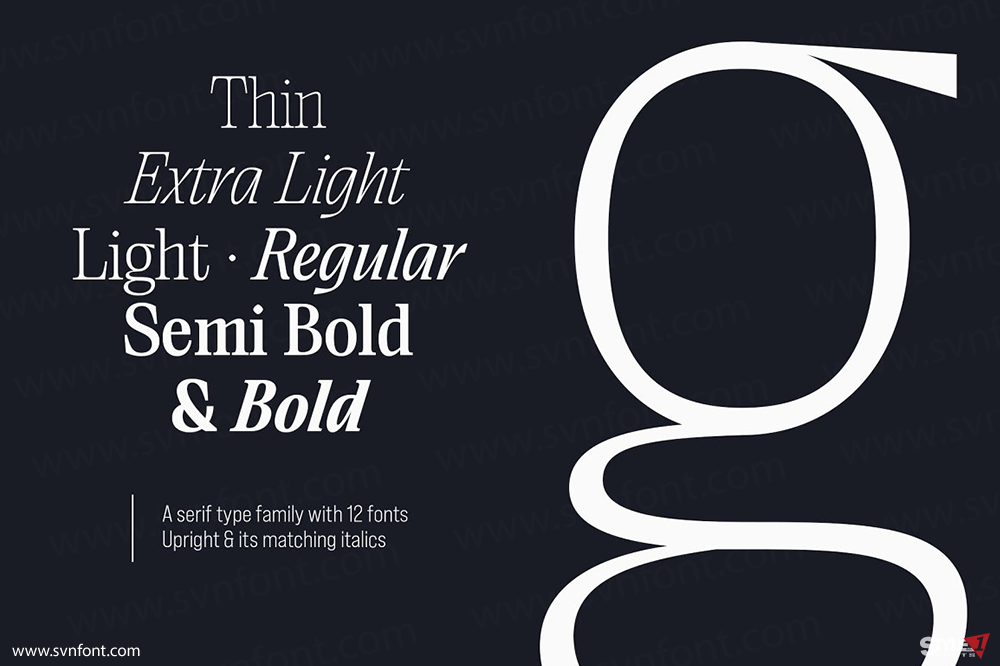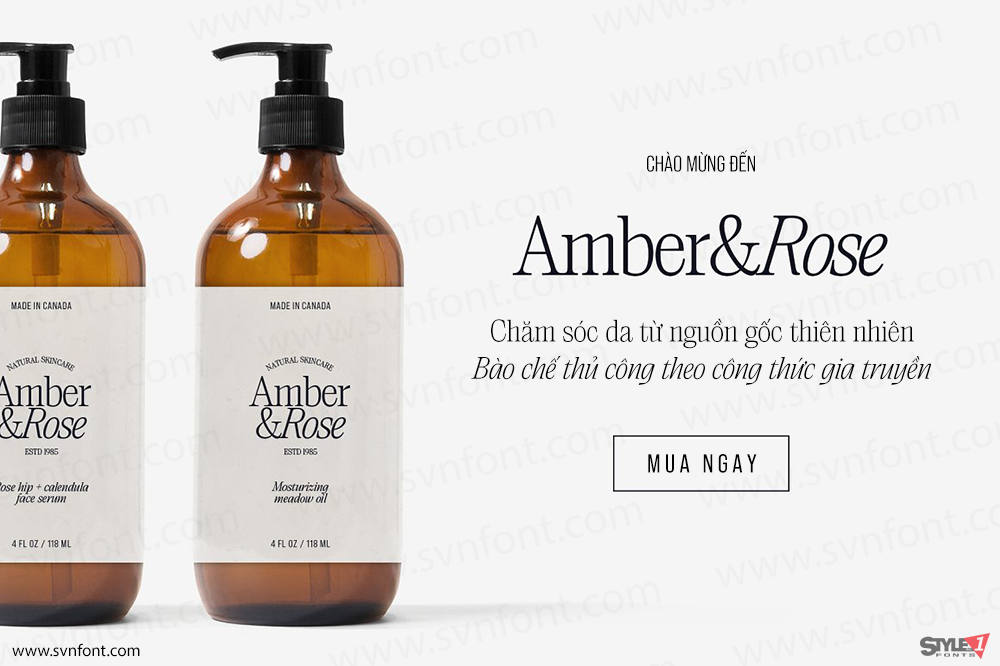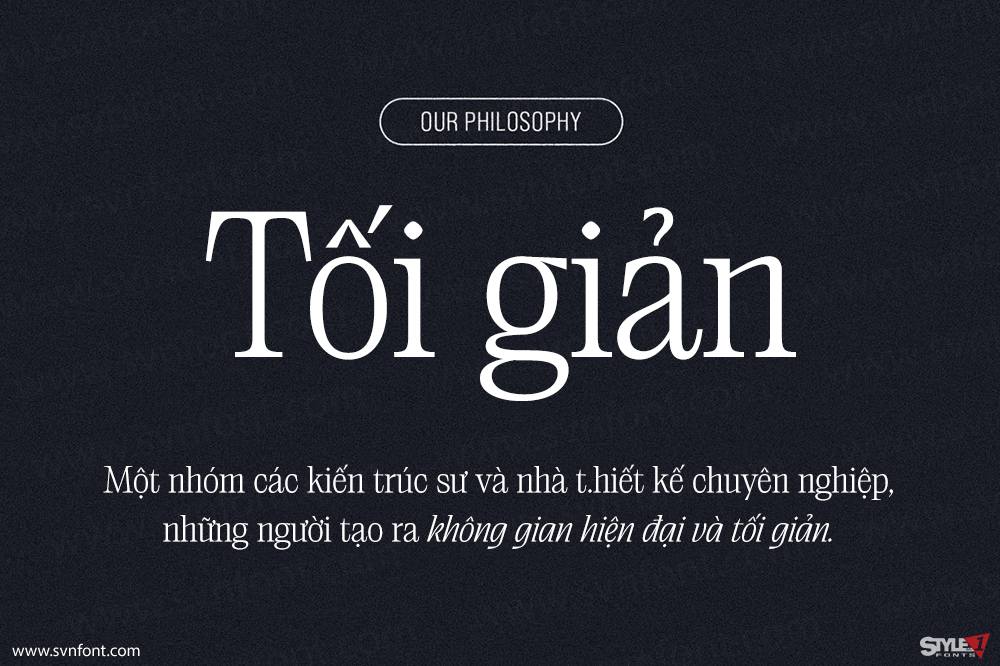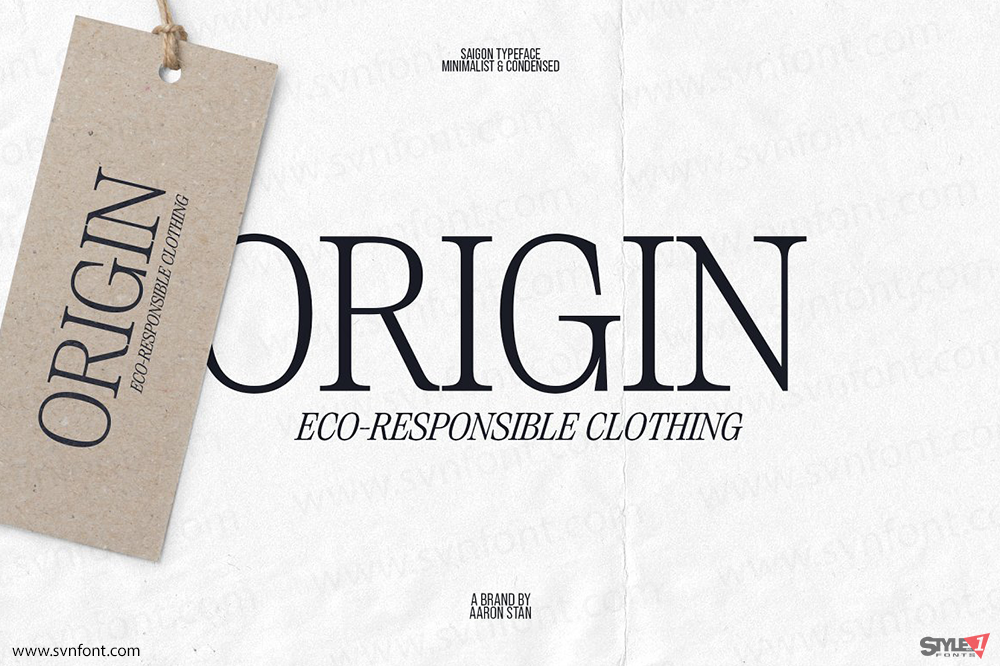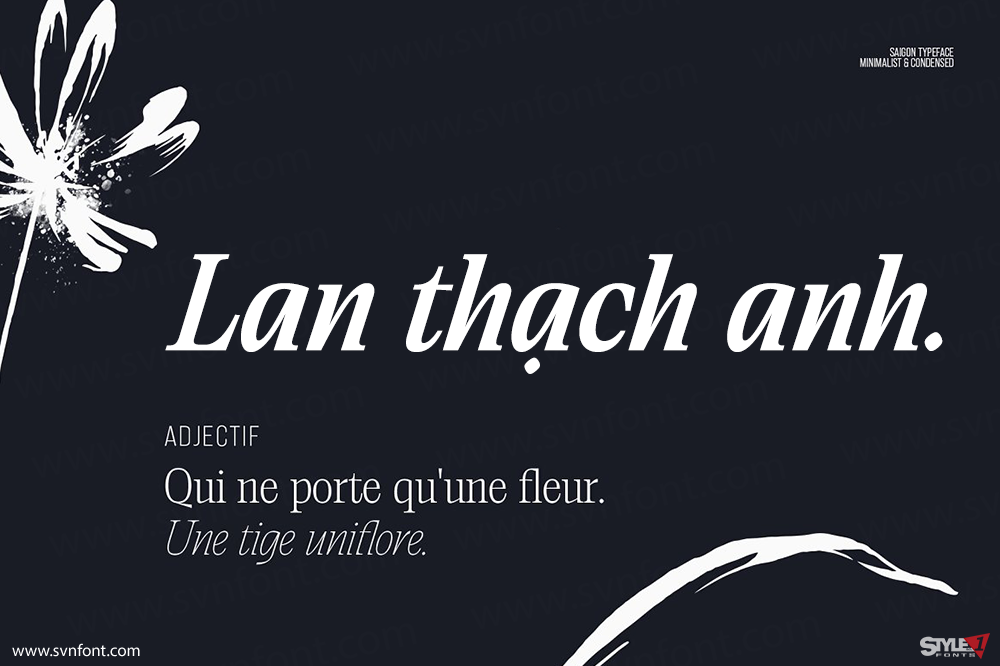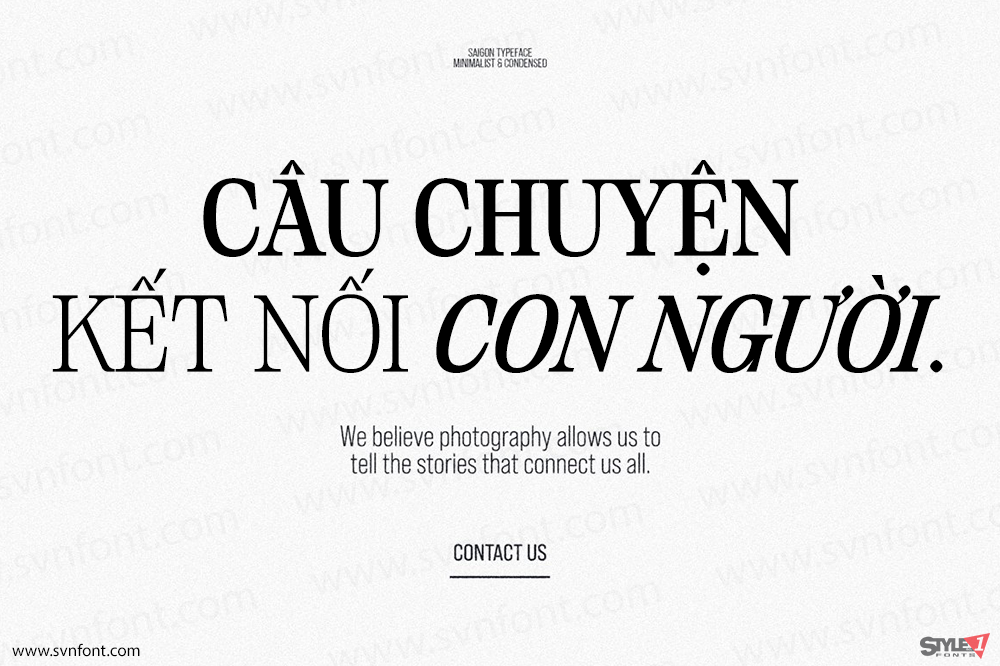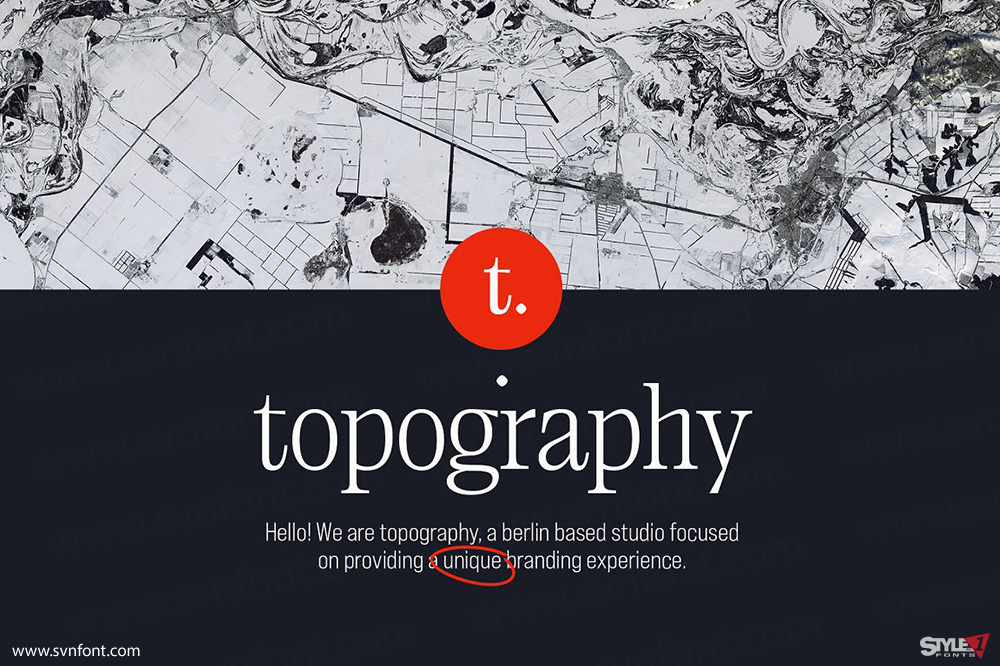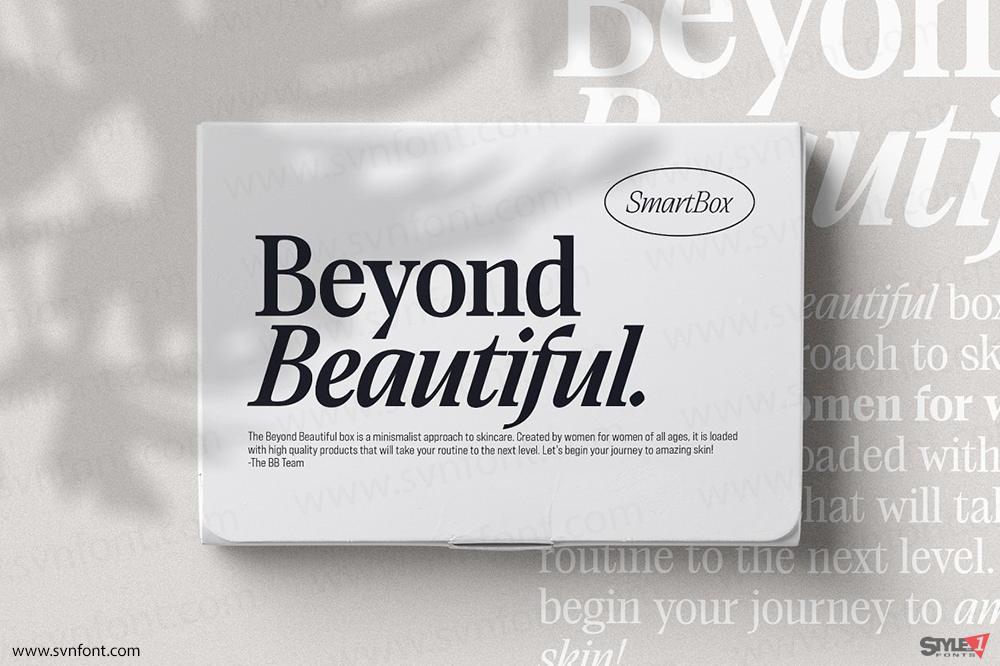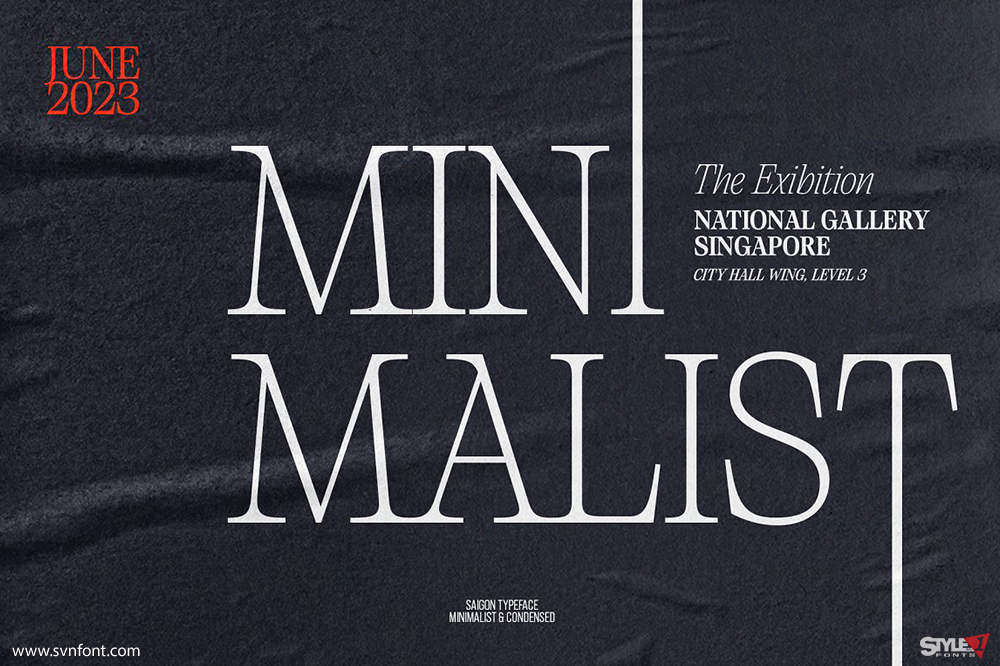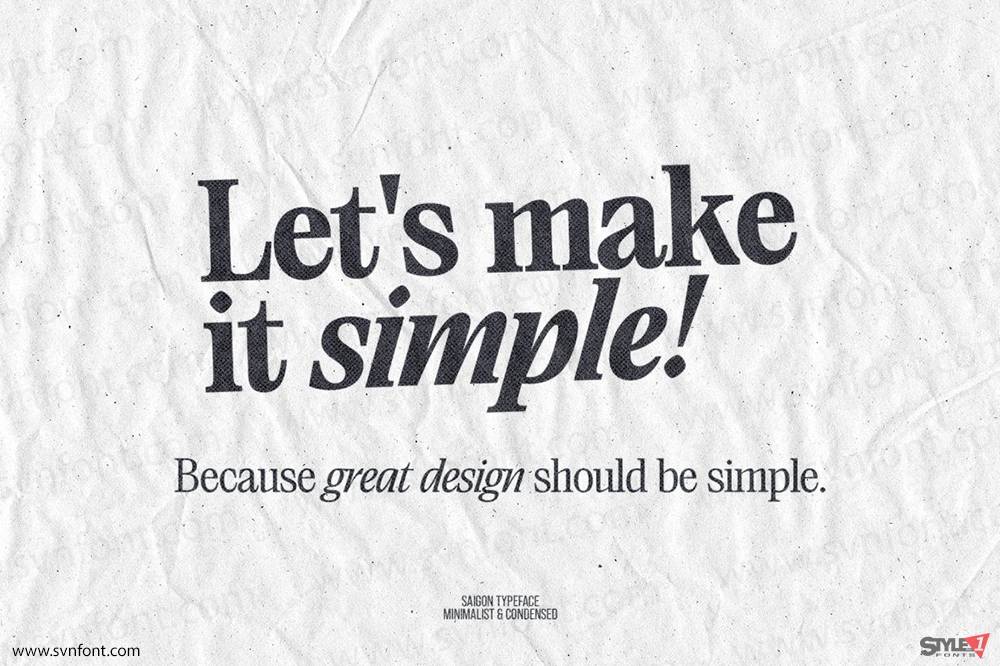
Saigon là một họ phông chữ serif cô đọng tối giản. Với những đường nét thanh thoát và các đường cong chặt chẽ, cá tính của nó nằm ở sự đơn giản, khiến nó trở thành một kiểu chữ biên tập vượt thời gian. Khi chữ nghiêng phá vỡ các nét truyền thống và mang một vẻ ngoài khiêm tốn nhưng hiện đại hơn, nó hòa quyện một cách hài hòa với phiên bản đứng, do đó tạo ra một nhịp điệu hài hòa làm nổi bật phong cách tối giản của Saigon.
Kiểu chữ serif có độ tương phản thấp này được tạo ra để trông tuyệt vời cả trong hiển thị và văn bản. Cho dù đó là các tiêu đề đậm hay các đoạn văn mô tả, Saigon hướng đến sự linh hoạt và tiện dụng nhất có thể. Nó cung cấp 6 độ đậm từ mỏng đến đậm, cho phép bạn nâng tầm thiết kế chữ của mình trong tích tắc mà vẫn giữ được sự đơn giản. Bởi vì thiết kế tuyệt vời nên đơn giản. Họ phông chữ này hỗ trợ các ngôn ngữ dựa trên chữ Latinh chính cùng với các tính năng OpenType như phân số, chữ số kiểu cũ, chữ ghép, dấu chấm câu phân biệt chữ hoa chữ thường, các ký tự thay thế cách điệu và hơn thế nữa.
Nhà thiết kế: Jessika Granell
Nhà phát hành: The Paper Town